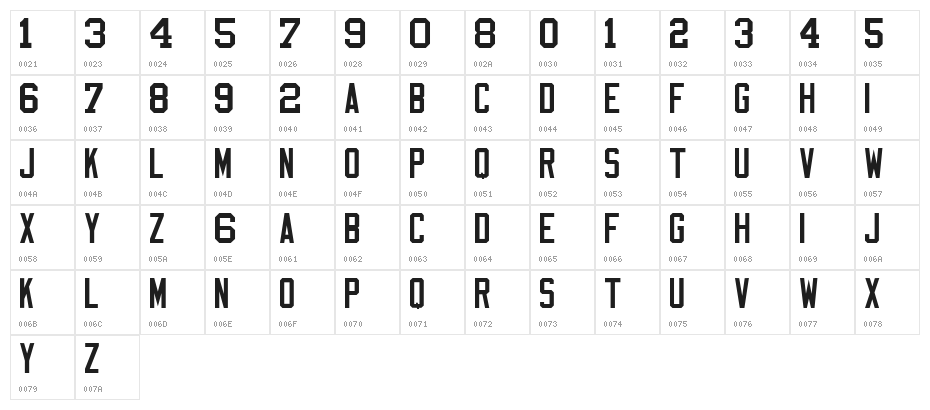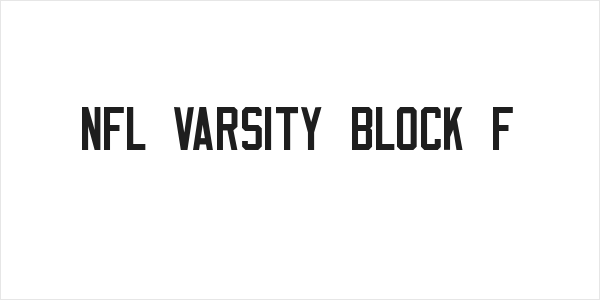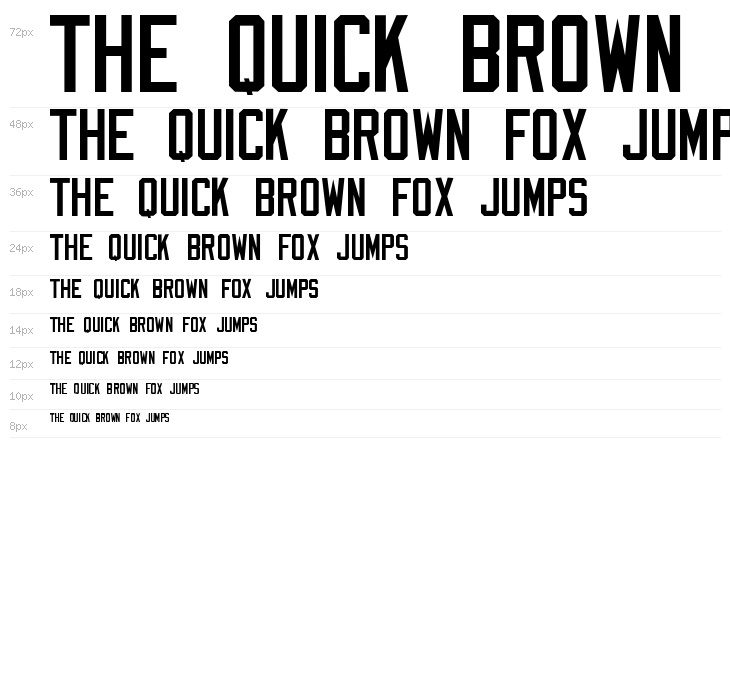
NFL Varsity Block F Font
| Proiecte propuse | Ideal for sports team branding, school merchandise, event posters, and any project requiring a bold, athletic aesthetic. |